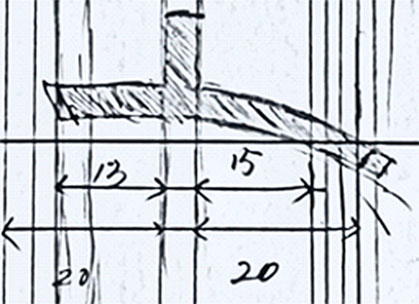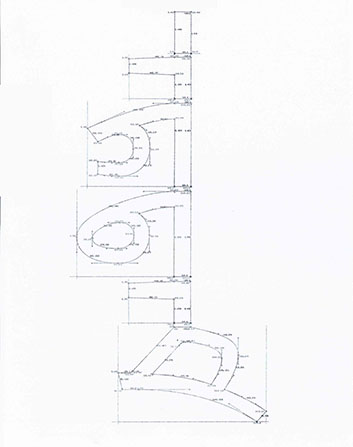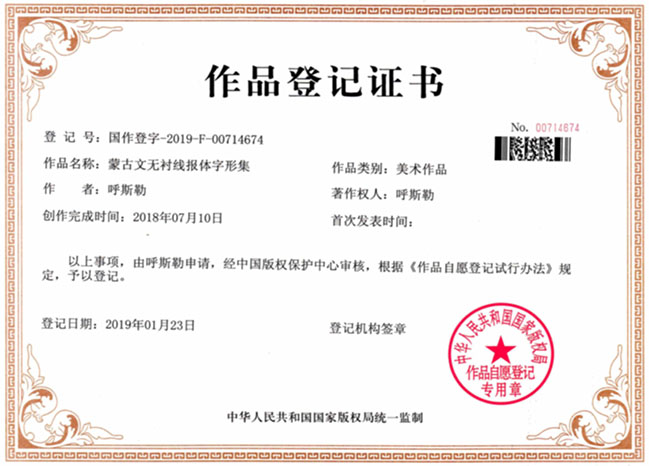
蒙古文无衬线报体研发过程
蒙古文无衬线报体100%原创,从初期字形设计到字体细节优化调整都是内蒙古社会科学院蒙古语 信息技术研发(MIT)中心的呼斯勒独立创作完成,且不存在抄袭、复制他人作品的情形。本字 体在中国国家版权局进行了版权注册登记,享受版权法保护。
第一步:根据灵感起草手写底稿确定字体风格
第二步:设计字体模板规范
第三步:电脑绘制矢量字体图形
第四步:扩展字符集